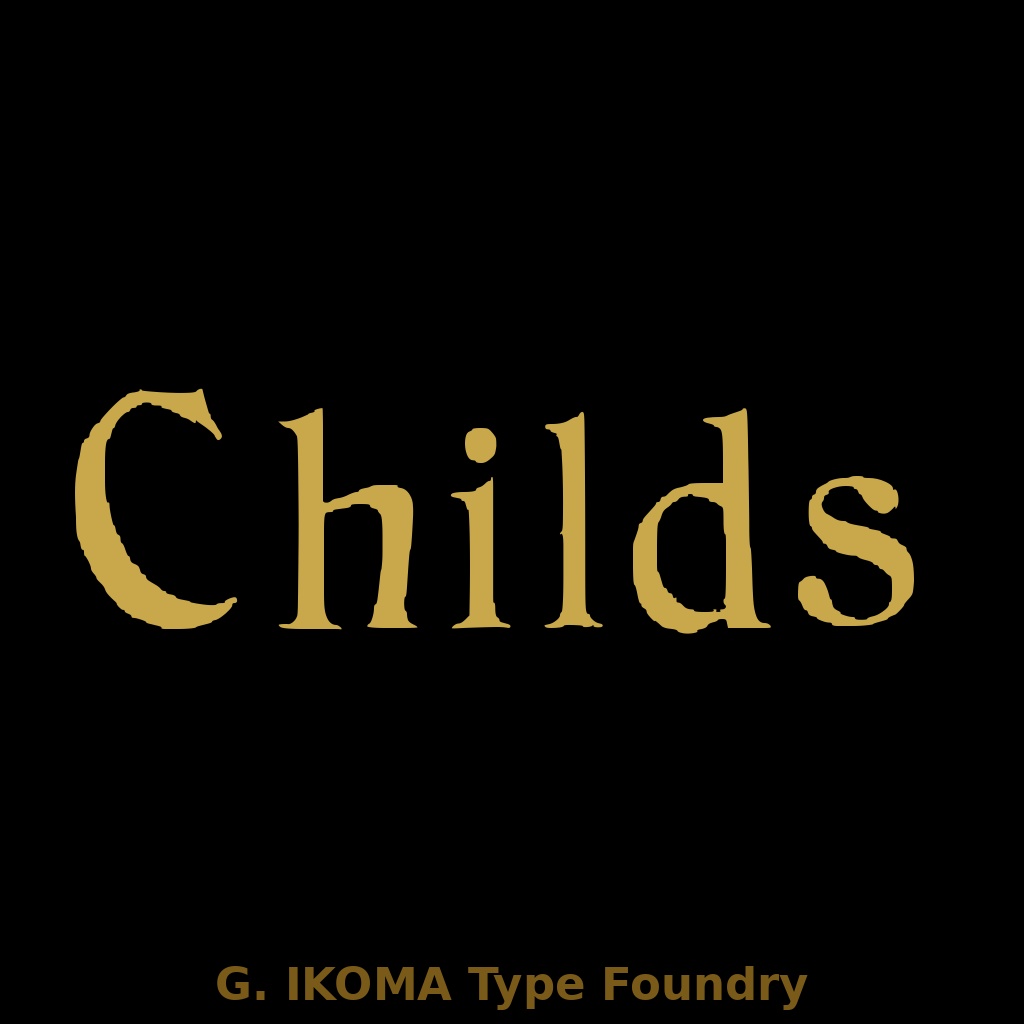
CHILDS — 19世紀欧州印刷資料復元フォント / Historical Revival Typeface [Art Nouveau]
━━━━━━━━━━━━━━━━━━━━━━━━━ 【フォントについて】 ━━━━━━━━━━━━━━━━━━━━━━━━━ CHILDS EXTENDED は、19世紀末〜20世紀初頭の欧州印刷資料を原典に、 手作業でトレース・デジタル化した復元フォントです。 本作は、American Type Founders' Co.(フィラデルフィア)が制作した Art Nouveau 様式の装飾書体「Childs」の復元です。 American Type Founders(ATF)は19世紀末から20世紀初頭にかけて 北米最大の活字鋳造連合として知られ、その書体はヨーロッパの印刷資料にも 広く収録・紹介されました。本フォントはそのドイツ語圏への紹介誌面をもとに デジタル復刻したものです。 原典:Ludwig Petzendorfer, "Schriften-Atlas" / "Schriften-Atlas: Neue Folge" Julius Hoffmann, Stuttgart(パブリックドメイン) 様式:Art Nouveau 収録グリフ:163文字(大文字・小文字・数字・記号) 欠落グリフ:なし 制作:株式会社生駒時計店 / G. IKOMA, LTD.(1870年創業) ━━━━━━━━━━━━━━━━━━━━━━━━━ 【ご購入前にご確認ください】 ━━━━━━━━━━━━━━━━━━━━━━━━━ 本フォントは Art Nouveau 様式特有の優雅な曲線と装飾的な字形を特徴とする ディスプレイ向け書体です。ロゴ・見出し・ポスターなど大きなサイズでの 使用に適していますが、本文組版や小サイズでの長文用途には向きません。 また、原典由来の字形をもとに再構成しているため、現代的な汎用書体のような 設計ではありません。 ━━━━━━━━━━━━━━━━━━━━━━━━━ 【収録内容】 ━━━━━━━━━━━━━━━━━━━━━━━━━ ・I_Childs_Extended.ttf ・LICENSE.txt(日英) ・thumb2_I_Childs_Extended.png(グリフチャート) ━━━━━━━━━━━━━━━━━━━━━━━━━ 【推奨用途】 ━━━━━━━━━━━━━━━━━━━━━━━━━ ・ロゴ ・ブランド名 ・ポスター・フライヤーの見出し ・書籍・雑誌のタイトル ・パッケージデザイン ・店舗サイン・看板文字 ・ウェディング・イベント案内状 Art Nouveau 特有の流麗な曲線と優美な装飾性が求められる用途に適しています。 本文組版・小サイズでの常用には向きません。 ━━━━━━━━━━━━━━━━━━━━━━━━━ 【ライセンス】 ━━━━━━━━━━━━━━━━━━━━━━━━━ 本フォントは、個人利用・商用利用を問わず、印刷物、画像、ロゴ、バナー、 動画サムネイル等の制作に使用できます。 また、WebサイトやSNSで画像化された状態で使用することは可能です。 ただし、以下の行為は禁止します。 ・フォントファイルそのものの再配布、再販売、譲渡、共有 ・改変したフォントファイルの配布 ・本フォントを素材集、テンプレート、デジタル商品等に収録して再販売する行為 ・本フォントファイルをWebフォントとしてサーバーに設置・配信して利用する行為 ・アプリケーション、ゲーム、ソフトウェア、電子機器等への埋め込み利用 ・AI学習、機械学習、生成モデル訓練等への利用 ・本フォント自体または収録字形そのものについて独占的権利を主張する行為 詳細は同梱の LICENSE.txt をご確認ください。 ━━━━━━━━━━━━━━━━━━━━━━━━━ 【原典資料について】 ━━━━━━━━━━━━━━━━━━━━━━━━━ 本フォントは、G. IKOMA, LTD. 所蔵の実物資料をもとに制作しています。 原典資料そのものは本商品に含まれていません。 資料アーカイブについては、下記サイトをご参照ください。 G. IKOMA Archive https://g-ikoma-archive.netlify.app/ ━━━━━━━━━━━━━━━━━━━━━━━━━ BOOTH: https://g-ikoma.booth.pm/